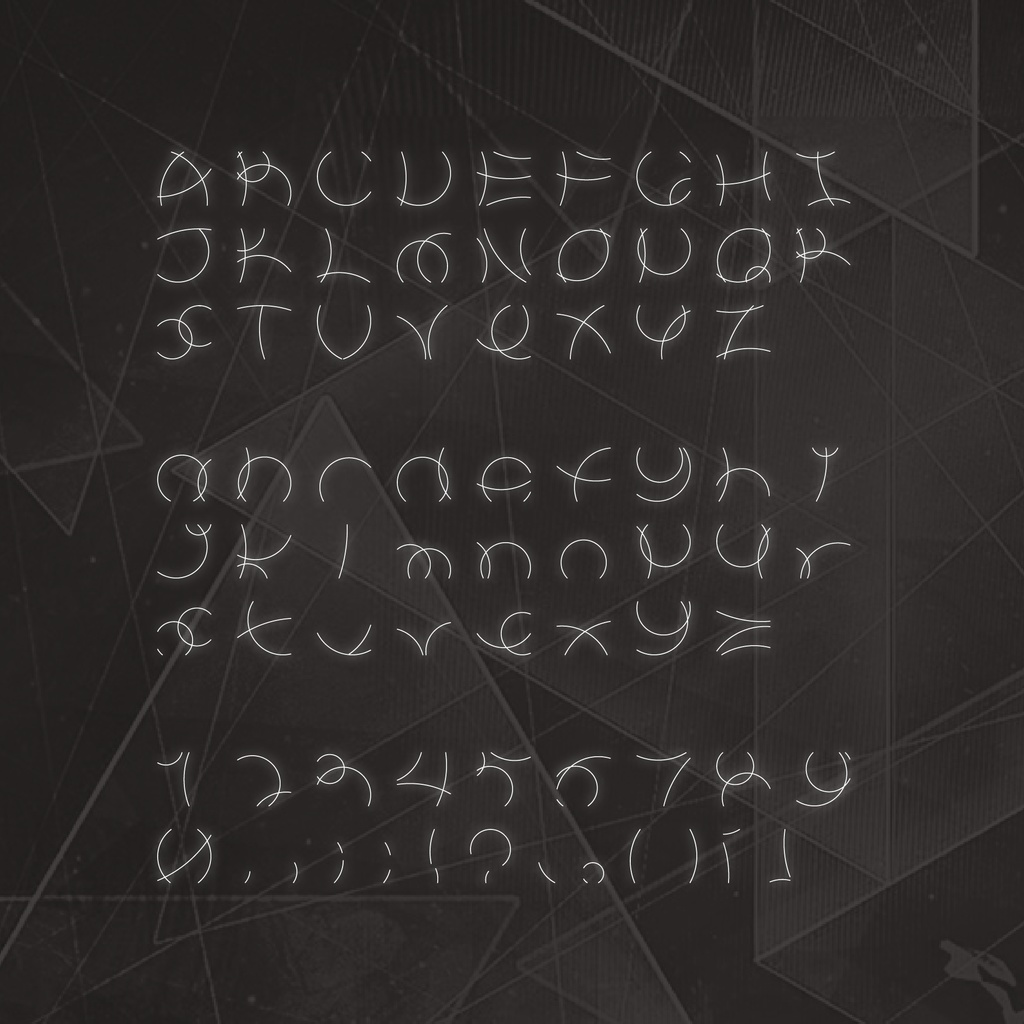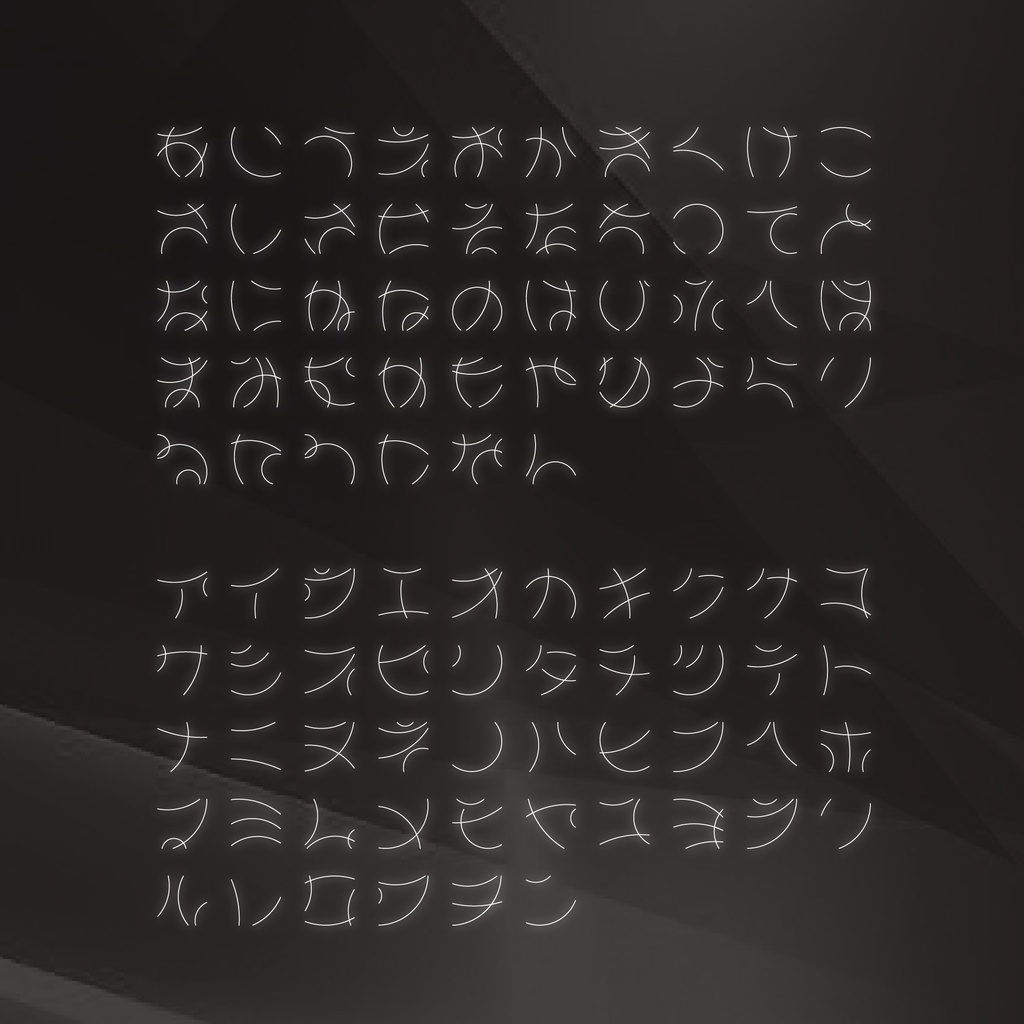
【日本語フォント】Linear ⧄「無料」
➰ Linear ⧄ ➰ 📢📢📢📢📢📢📢📢📢 特記事項 📢📢📢📢📢📢📢📢📢 リツイートで新フォントを配布する企画を開催中。 📢新しいフォントが掲示ツイートが目標達成から1ヶ月間のみ無料配布され、その後は有料となりますが。また、配布開始ツイートが毎回100RTの倍数を超えると、まだ1ヶ月間無料でDLできます。📢 ☕️価格設定には、集中力を維持するために、缶コーヒーに依存しているです。 そのため、大体の制作日数×日本での缶コーヒーの値段でフォントの価格を算出することにします。☕️ 📢📢📢📢📢📢📢📢📢 デザイン説明 📢📢📢📢📢📢📢📢📢 最初はこの作品を1日で完成予定。時間が大変かかるましたが、そしで最近は漢字フォントの作成が中心なので、このフォントに過度な期待はしないで下さいね。 このフォントには2つの使い方があります。 フレーム付きバージョンを使用すると、ネオンの装飾が施された抽象的なフォントのように見えます。 フレームなしバージョンを使用すると、スクリーン上の繊維や髪の毛のように見える、非常に抽象的なフォントになります。 📢📢📢📢📢📢📢📢📢 利用規約 📢📢📢📢📢📢📢📢📢 個人、商用どちらでも利用可能です。 ✨フォントが使用されたら、ツイッターにお知らせくださいhttps://twitter.com/amari_design✨ 本素材を使用した作品については、リツイートなどの形で宣伝させていただく場合があります。 フォントのインストール等の技術的なサポートはいたしません。使用して発生したと思われる如何なる問題についても、作者は責任を負わないものとします。 著作権を放棄することはありません。 商標を登録したり、作者であると主張したり、データ自体を販売または再販したりすることは禁じられています。 このコンテンツの最終的な解釈権は作者に帰属します。 内容補充とバージョン更新は製作続けるです。使用する際は最新バージョンにご注意ください。 📢📢📢📢📢📢📢📢📢 収録內容 📢📢📢📢📢📢📢📢📢 ラテン文字、数字、仮名だけてを含む295グリフが含まれています。 ーーーーーーーーーーーー Twitter:https://twitter.com/amari_design Behance:https://www.behance.net/9f45706b ーーーーーーーーーーーー